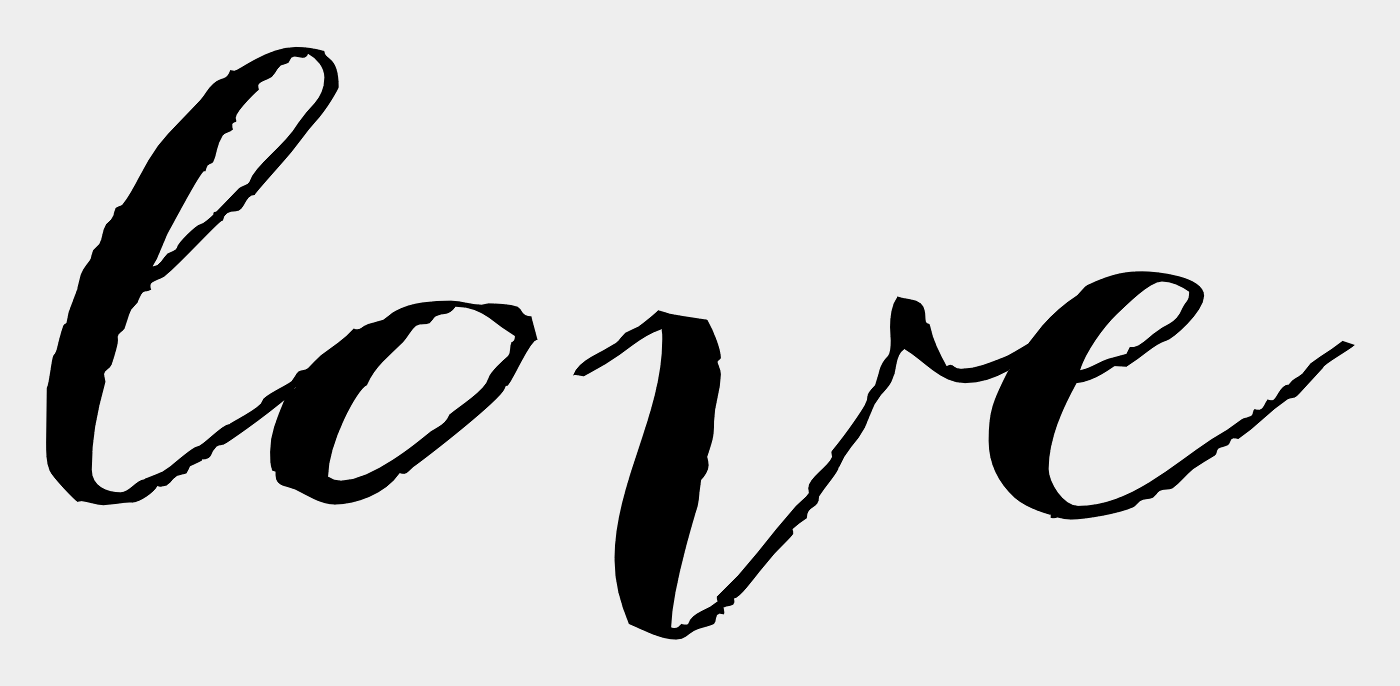
Welche Schrfitart is das? (love)
Kann mir ein Experte sagen welche Schriftart das ist auf dem Bild :)
So eine ähnliche Frage hatte ich auch mal. Leider ist es oft nicht möglich, solche Script-Fonts zu identifizieren, da sie zur Zeit sehr im Trend sind.
Du kannst aber selbst mal auf die Suche gehen, nach einer Schrift, die dir gefällt und deinen Ansprüchen entspricht:
Edit: Empfehlen kann ich dir die kostenlose Bromello, die deinem Beispiel schon recht nahe kommt.
Ich meine mich hier zu erinnern, das wir genau diese Schrift hier schon mal identifiziert hätten. Auch habe ich sie gerade in einer Werbung im Fernsehen gesehen. Da ich bei Werbung eher weg höre, kann ich mich grad nicht an die beworbene Marke erinnern.
Die Bombshell Pro hat über 800 Glyphen mit allerlei Buchstabenvarianten, auch für Anfang, Ende, Mitte und so weiter, damit sie handschriftlicher daherkommt. Daher auch das hier in der Darstellung abweichende "v".